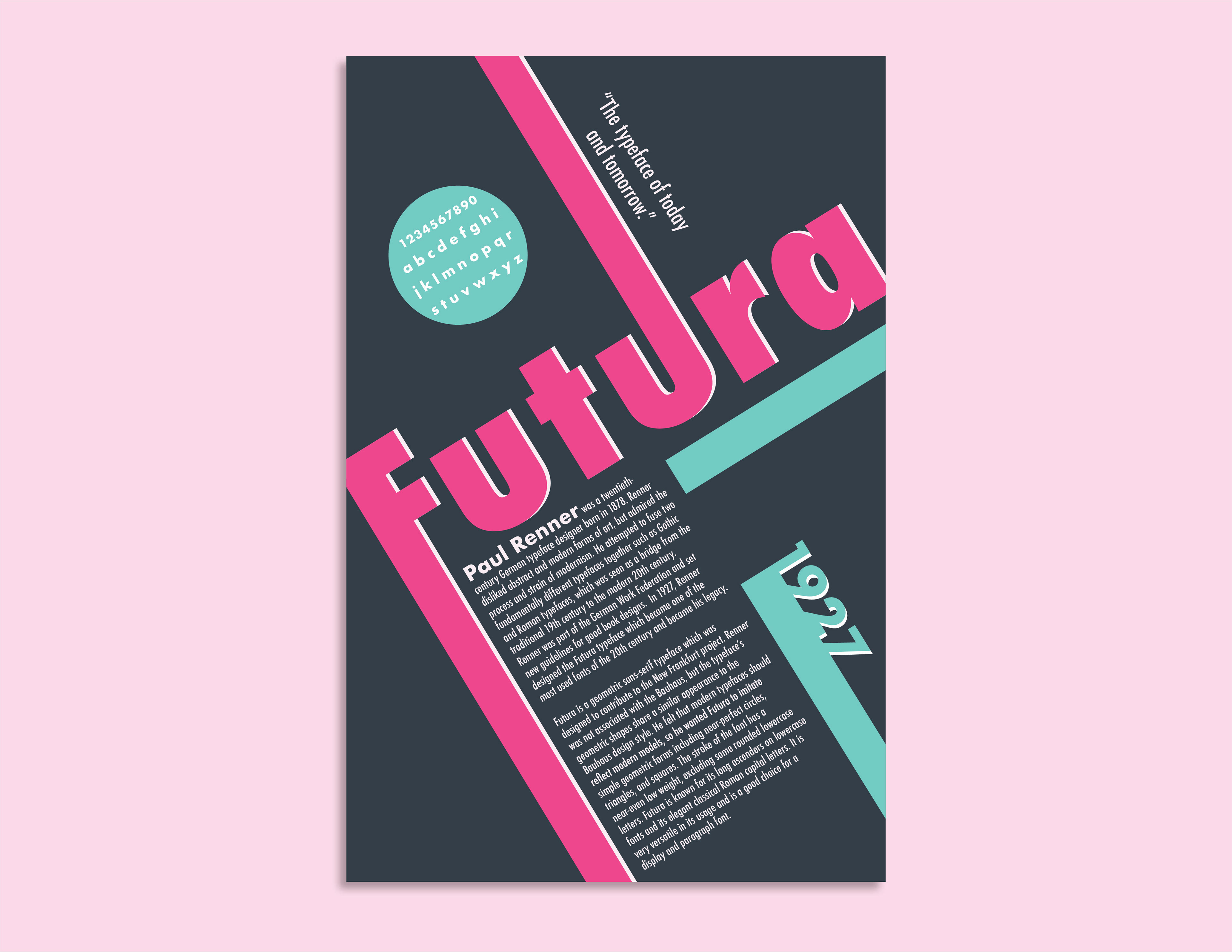
Khi nhắc đến các font chữ hiện đại, Futura là một cái tên không thể thiếu trong ngành thiết kế đồ họa. Với những đường nét cứng cáp, hình học chính xác, font Futura luôn được các nhà thiết kế ưa chuộng. Phiên bản Việt hóa của Futura càng làm tăng tính linh hoạt của font này, giúp nó dễ dàng ứng dụng trong các dự án thiết kế tại Việt Nam. Bài viết này sẽ giúp bạn hiểu rõ hơn về đặc điểm và ứng dụng của font Futura Việt hóa cho các dự án thiết kế của mình.
Được thiết kế bởi Paul Renner vào năm 1927, Futura đã trở thành một trong những font chữ không chân (sans-serif) phổ biến nhất, mang đậm ảnh hưởng của phong trào Bauhaus.
Được Việt hóa bởi SFU, font Futura có một bộ sưu tập các kiểu chữ đa dạng với nét mỏng và nét dày, phù hợp với nhiều mục đích sử dụng khác nhau. Các kiểu chữ này có sự linh hoạt trong việc tạo ra các hiệu ứng thẩm mỹ và phù hợp với các thiết kế yêu cầu sự chính xác, rõ ràng và hiện đại.
Các kiểu chữ có nét mỏng trong font Futura Việt hóa mang lại cảm giác thanh thoát, nhẹ nhàng nhưng vẫn rất cứng cáp và chuyên nghiệp.
Futura Light và Futura LightOblique: Đây là những kiểu chữ có nét mỏng, thanh thoát, tạo cảm giác nhẹ nhàng.
Futura Regular và Futura Oblique: Đây là các kiểu chữ với nét mỏng nhưng có độ dày tương đối ổn định, tạo sự cân đối và dễ đọc.
Futura Book và Futura BookOblique: Các kiểu chữ này mang đến một cảm giác chắc chắn. Chúng không quá mảnh như Futura Light, nhưng vẫn giữ được sự thanh thoát cần có.
Các kiểu chữ có nét dày của Futura font Việt hóa mang đến một cảm giác mạnh mẽ và cứng cáp. Đây là những lựa chọn lý tưởng cho những thiết kế đòi hỏi sự nổi bật và rõ ràng.
Futura Heavy và Futura HeavyOblique: Những kiểu chữ này có nét dày và vững chắc, tạo sự ấn tượng mạnh mẽ ngay từ cái nhìn đầu tiên.
Futura Bold và Futura BoldOblique: Đặc trưng bởi các nét chữ đậm, mạnh mẽ, Futura Bold mang đến một sự táo bạo, dễ dàng thu hút sự chú ý. Khi kết hợp với phiên bản BoldOblique, font này không chỉ đậm mà còn có độ nghiêng tạo thêm phần năng động và lôi cuốn.
Futura ExtraBold và Futura ExtraBoldOblique: Đây là những kiểu chữ mạnh mẽ nhất trong bộ sưu tập Futura, với độ dày vượt trội. Futura ExtraBold là font chữ lý tưởng cho những thiết kế cần sự “bùng nổ” và thu hút sự chú ý ngay lập tức.
Nhờ vào sự linh hoạt trong các kiểu chữ nét mỏng và dày, font Futura Việt hóa có thể được áp dụng rộng rãi trong nhiều lĩnh vực thiết kế khác nhau. Dưới đây là một số ứng dụng phổ biến của font này trong các ngành nghề yêu cầu sự cứng cáp, vững chãi và mạnh mẽ.
Font Futura Việt hóa đặc biệt phù hợp với các thiết kế liên quan đến ngành xây dựng, vì nó mang lại cảm giác vững chắc và ổn định. Những kiểu chữ Bold hay Heavy có thể được sử dụng trong thiết kế logo của các công ty xây dựng, các bảng hiệu công trình hay các tài liệu marketing cho doanh nghiệp xây dựng.
Trong ngành thể thao điện tử (Esports), việc thiết kế logo cho các đội tuyển, tên các giải đấu hay các sản phẩm liên quan đến game đòi hỏi sự nổi bật và dễ nhận diện. Font chữ to đậm, đặc biệt là các kiểu như Futura ExtraBold và Futura BoldOblique, rất thích hợp cho những thiết kế này. Chúng giúp tạo ra sự mạnh mẽ và năng động, đồng thời dễ dàng thu hút ánh nhìn của người chơi và khán giả.
Ngành cơ khí đòi hỏi sự chính xác và mạnh mẽ trong các thiết kế logo, tên thương hiệu hoặc các tài liệu kỹ thuật. Font chữ cứng cáp như Futura Heavy và Futura ExtraBold sẽ tạo ra sự vững chắc và chính xác cho các thiết kế trong lĩnh vực này.
Như vậy, font Futura Việt hóa là một lựa chọn tuyệt vời cho các dự án thiết kế cần sự hiện đại, mạnh mẽ và dễ nhận diện. Với bộ sưu tập các kiểu chữ mỏng và dày, Futura mang lại sự linh hoạt trong thiết kế, phù hợp với nhiều ngành nghề và lĩnh vực khác nhau. Dù bạn đang làm việc trong ngành xây dựng, thể thao điện tử, cơ khí hay bất kỳ ngành nghề nào khác, font Futura Việt hóa đều có thể giúp bạn tạo ra những thiết kế ấn tượng và đầy sức mạnh. Hãy tải xuống và bắt đầu sử dụng font Futura Việt hóa cho các dự án thiết kế của bạn ngay hôm nay!